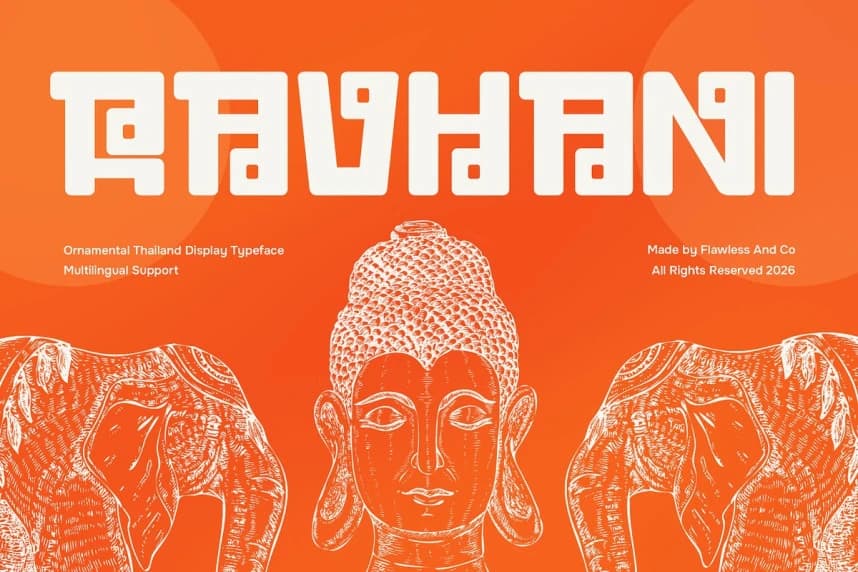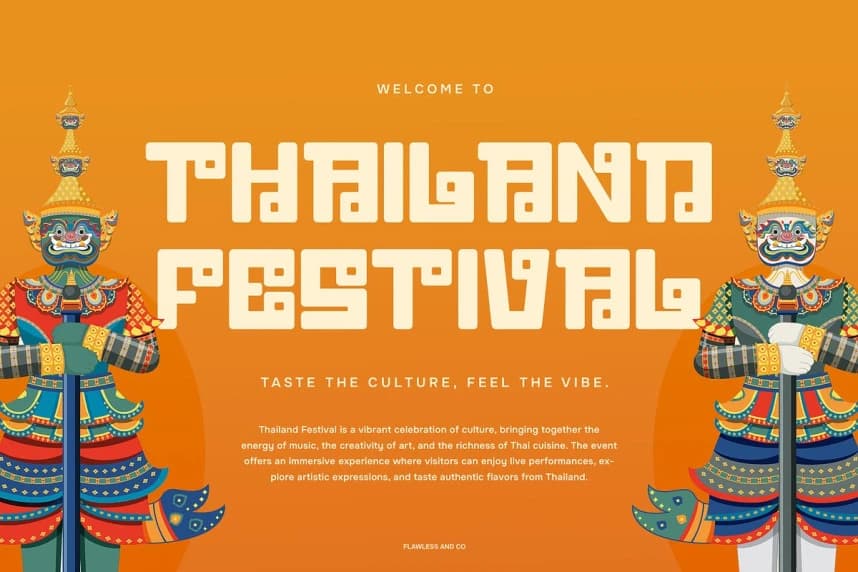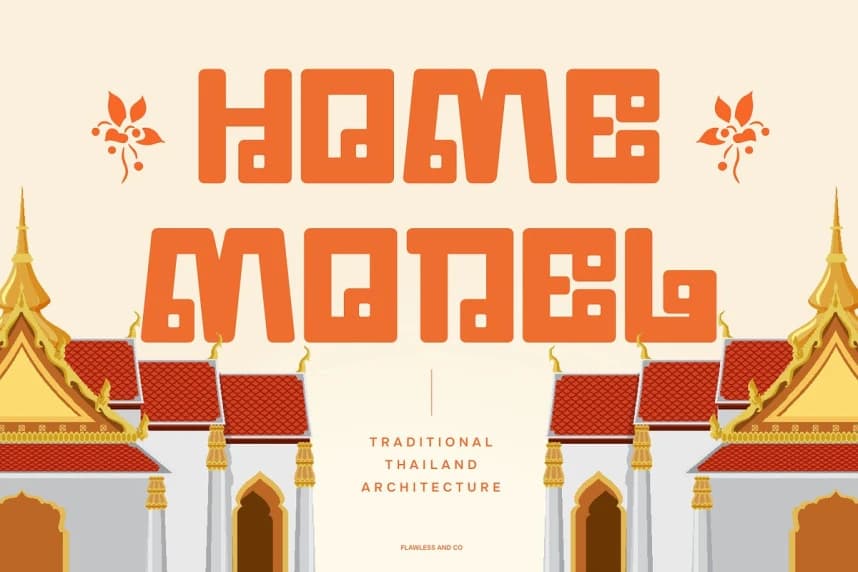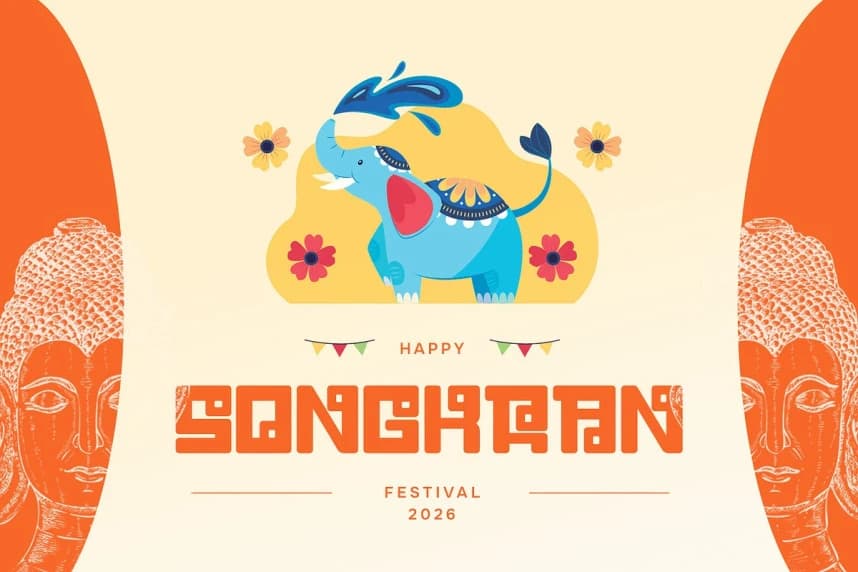
Ravhani Font
Ravhani Font, Tayland'ın doğulu bir gösteri yazı tipidir ve zarif ve süsleyici harf biçimleriyle Tayland kültürel estetiğinin zenginliğini yansıtır. Geleneksel Tayland sanatı ve görsel öğelerden ilham alınmıştır.
Ravhani Font, Tayland için Doğu etkilerini yansıtan zarif ve dekoratif harf biçimleriyle bir gösterim yazı tipidir. Geleneksel Tayland sanatı ve görsel öğelerden ilham almıştır.